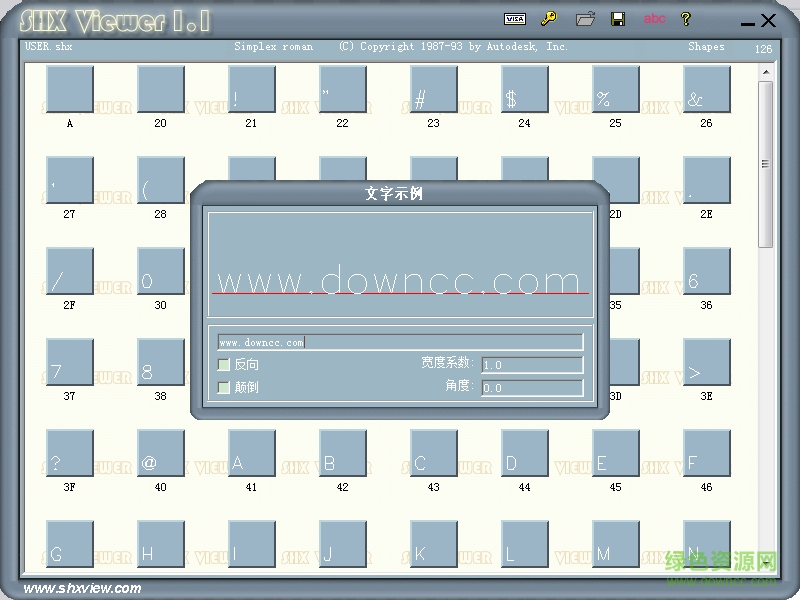
user.shx形字體
user.shx是cad 3D制圖軟件中必不可少的一款字體文件,安裝字體后可以正常的讀取頁(yè)面信息,此款字體字型結(jié)構(gòu)簡(jiǎn)單易讀,字體豐富完整,全面支持各大cad軟件,歡迎來(lái)綠色資源網(wǎng)下載!
user.shx形字體介紹
user.shx是CAD軟件中的一種字體,用于顯示鋼筋符號(hào)。如果制圖者在作圖時(shí)使用了鋼筋符號(hào),而打開(kāi)圖紙的電腦里面沒(méi)有安裝可以顯示鋼筋符號(hào)的字體時(shí),就會(huì)提示需要安裝字體,否則無(wú)法顯示出來(lái)。一般而言,只需要安裝了能夠顯示鋼筋符號(hào)的字體都可以正常打開(kāi)的,小編經(jīng)過(guò)幾番分析比較發(fā)現(xiàn)user.shx這種字體,既可以滿足需求又可以節(jié)省空間(因?yàn)榘惭b包才7KB),特此分享給大家,希望能夠幫助到大家。